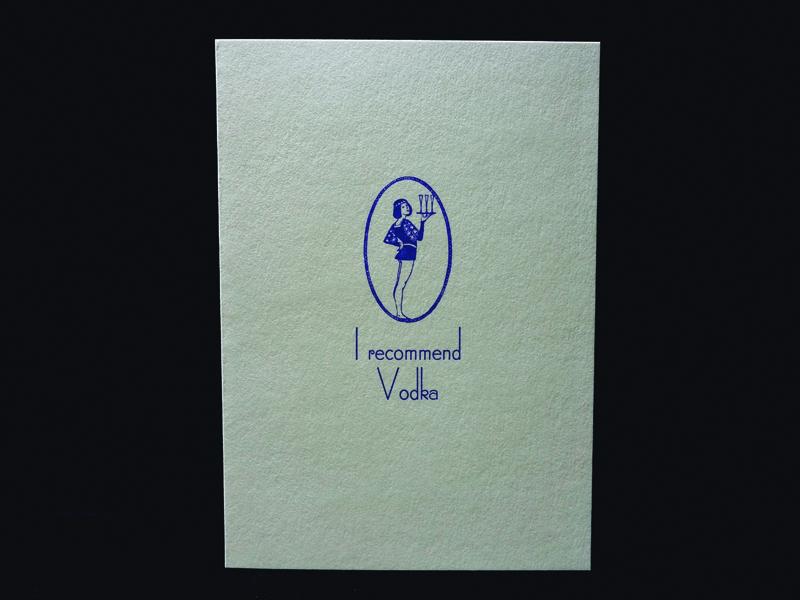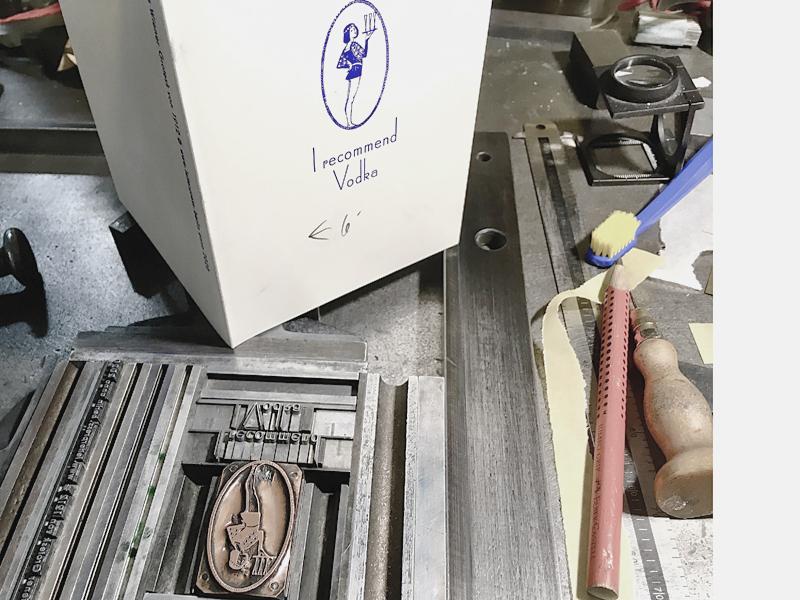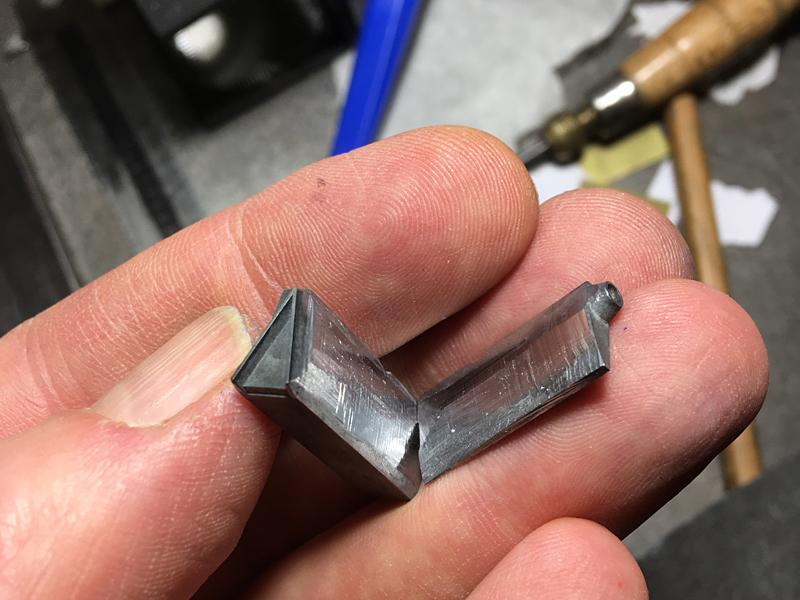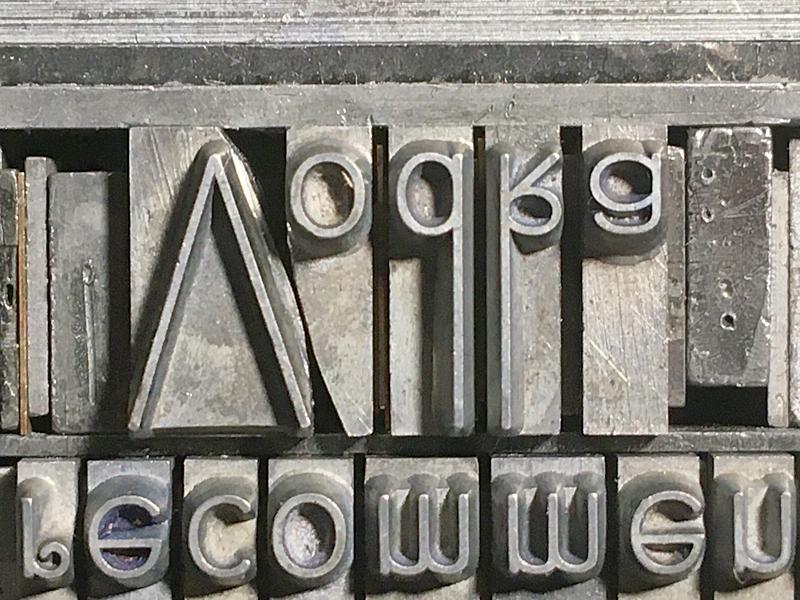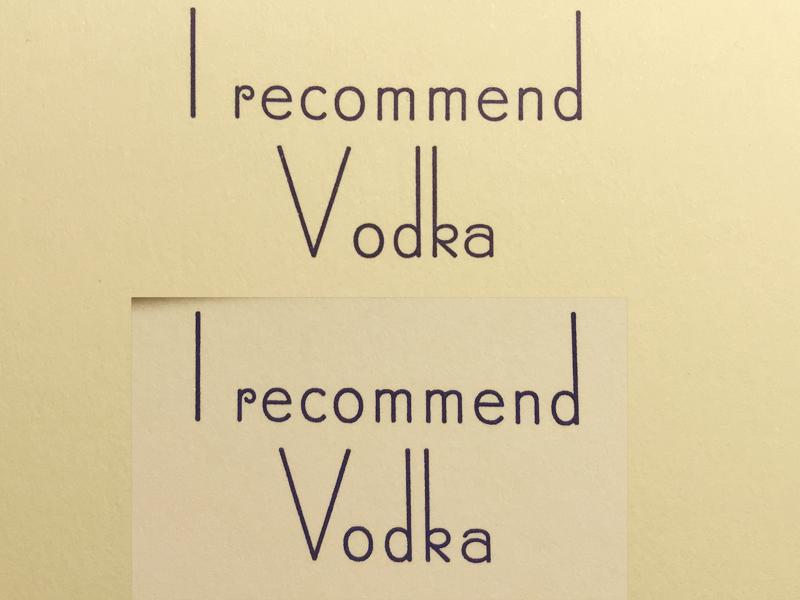
Mir fehlten bei den vorangegegangen Auflagen Zeit und Mut, diese seltene und empfindliche Schrift mit einer Feile anzufassen. Aber nun habe ich es gewagt. Vielleicht auch, weil ich beim digitalen Satz oft eingreife und dadurch empfindlicher geworden bin. 3238.jpg
Hier steht die Form auf der Schließplatte. Wenn man als Setzer und Drucker allein in der Werkstatt arbeitet, kann man sich den Arbeitsplatz aussuchen. Früher hätte der Setzer die Arbeit im Winkelhaken gemacht, weil der Drucker seinen Platz selbst brauchte.
Das Unterschneiden ist gefährlich für das Schriftbild. Eine falsche Bewegung, und der Buchstabe ist hin. Bei einer seltenen Schrift wie der Wiener Grotesk, Erstguß 1912, wäre das bedauerlich. Das Feilen dauert seine Zeit. Bis die Form paßt, vergeht ein Stündchen. Und wenn man den Buchstaben am Ende doch kaputt macht, werden zwei Stunden daraus. Ich war aber sehr vorsichtig und hatte Glück dazu.
Die beiden angefeilten Typen in der Druckform. Für Bleisatzkritiker: Das Blindmaterial links und rechts besteht aus Doppelcicero-Quadraten, weil die schneller greifbar waren als der Doppelmittel-Ausschluß. Hält auf kurzen Abschnitten genauso gut:
Schließlich die Vorher-Nachher-Ansicht:
Danke, dass du uns hier das Unterschneiden auch einmal im wahrsten Sinne des Wortes demonstriert hast. Und ja, diese Arbeit hat sich gelohnt. Ich habe mir diese Seite in meine Dauer-Lesezeichen gepackt, wenn mich mal wieder jemand fragt, warum das "Unterschneiden" heißt.
Gern geschehen. Der wahre Wortsinn ging mir beim Feilen durch den Sinn: entweder wird das Wort »schneiden« in einem vielleicht älteren Wortsinn benutzt, daß man überhaupt damit das Entfernen bezeichnete, oder es ist ein Begriff aus der alten Schriftgießerei, wo Überhang vielleicht mit einem speziellen Werkzeug hergestellt wurde, oder der Setzer hatte früher ein anderes Werkzeug. Mit dem Messer kann man an den Typen auch nur schaben, sonst, also wenn man wirklich schneidet, Druck anwendet mit einer Klinge, besteht die Gefahr, daß man sie im ganzen verformt. Ich hab auch schon an Brotschriftgraden unterschnitten, da vielleicht auch mit einem Messer. Ich kenne es nicht aus meiner Ausbildung und Praxis als angestellter Setzer. Wir haben so etwas nicht gemacht, es war immer schnell und billig gewünscht. Vielleicht ist es aber auch nur eine Versinnbildlichung. Weil Unterschneiden, also das Schneiden unter das Schriftbild mit dem Ergebnis, daß etwas fehlt, besser klingt als Unterfeilen oder Unterschleifen. Ich wüßte es gern genauer, falls jemand da mal was gelesen hat ...
Wenn es die Größe zulässt, ist aber rechtwinkliges Feilen vorzuziehen. Der große Vorteil ist dann, dass beide Buchstaben einen hinreichend großen Teil ihrer rechtwinkligen Seiten behalten und so auch weiterhin leicht mit anderen Buchstaben kombiniert werden können.
Hier ein sehr grob geschnittenes Beispiel, das ich gerade als Foto zur Hand hatte. Nicht schön geschnitten, aber links oben bleibt hinreichend viel Seitenkante stehen. Mit dem obigen V wäre das theoretisch auch möglich gewesen.
Theoretisch, ja. Praktisch hätte es sehr viel länger gedauert, größer ist die Gefahr des Unglücks (einmal abrutschen macht stundenlange Arbeit wertlos), und ich hätte mir andere Werkzeuge beschaffen müssen. Mit einer groben Eisenfeile lassen sich solche Stufen nicht in kleine Lettern feilen. Da kleine e konnte ich ja kaum in den Fingern halten. Das Satztechniklexikon von Herrn Niel erwähnt Unterschneidemaschinen, die gefräst und geschliffen haben. Ich hab so etwas nie gesehen. Motorsägen hatten wir nur für Maschinensatz, fürs Unterschneiden und Fräsen hatten die keine Vorrichtung, soweit ich mir entsinne. Das waren ziemlich grobe Geräte.
Die Letter auf dem Foto sieht aus wie zurechtgemacht für den Gebrauch als Initial, nicht um dort Kleinbuchstaben einzusetzen, denn das P wird an sich nicht unterschnitten. Das Problem hat man, wenn ich jetzt richtig denke, an sich nur mit V und W und bei Kursiven. Läßt sich das noch nachvollziehen? Sind im Schriftkasten auch abgeschnittene Kleinbuchstaben?
Das waren ziemlich grobe Geräte.
Da würde sich die Investition in einen Dremel oder Nachbau lohnen.
Sehr gute Idee, danke! Ich hab neulich einen Acrylstich mit einem Dremel flacher gemacht. Das war zwar eine Schweinerei (Späneflug), aber es ging sehr fix und genau. Überlege ich mir beim nächsten Störbuchstaben. So etwas kommt nur selten vor.
Wobei mir noch einfällt, arbeitet Ihr mit Absaugvorrichtungen?
Kenne ich nur vom Maschinensatz, um den Dunst vom Bleitopf abzuziehen. Beim Feilen von Hand atme ich nicht so dicht vor der Feile, sauge aber hinterher gründlich. Beim Dremeln müßte man das doch noch mal bedenken. Da kann ich aus meinem Industriestaubsauger was basteln. Danke für die Ideen!
Wenn man eine freie Hand hat kann man den Staubsauger ran halten. Macht aber nur Sinn, wenn der auch feine Partikel zurückhalten kann. Ansonsten den Schlauch im Schraubstock oder mit Schraubzwingen fixieren.
Schön hätte ich gefunden, wenn die Oberlängen von d und k direkt bündig mit m und m in der oberen Zeile wären. Davon abgesehen hat sich der Aufwand des Unterschneidens auf jeden Fall gelohnt ...
Entschuldigung, nur damit hier keine Mißverständnisse entstehen: Unterschnitten, um kleine, also auf Mittellänge stehende Kleinbuchstaben rechts besser anzuschließen, werden allenfalls T, V, W und Y. Es gibt einige Bleischriften, da haben diese Buchstaben Überhänge, da muß man dann bei den Minuskeln mit Oberlänge aufpassen, sonst macht es beim Ausschließen im Winkelhaken (beim Zusammenpressen der Zeile) knacks, und der Überhang bricht weg. Das von Ralf oben beispielhaft gezeigte P wurde nicht für einen gewöhnlichen Textsatz unterschnitten. Vielleicht hat man das als Initial benutzt oder auch einen Punkt, das Satzzeichen für eine Abkürzung, enger setzen wollen. Aber gewöhnliche Minuskeln auf Mittellänge lassen sich in den wenigsten Schriften unter ein P oder auch F schieben. Also wenn wir von Antiqua sprechen. Bei Schreibschriften sieht es freilich anders aus, da können die Überhänge und die Bearbeitungsmöglichkeiten ganz bizarr sein. Das sind aber Ausnahmen. Bei F wird nüscht »gefräst«.